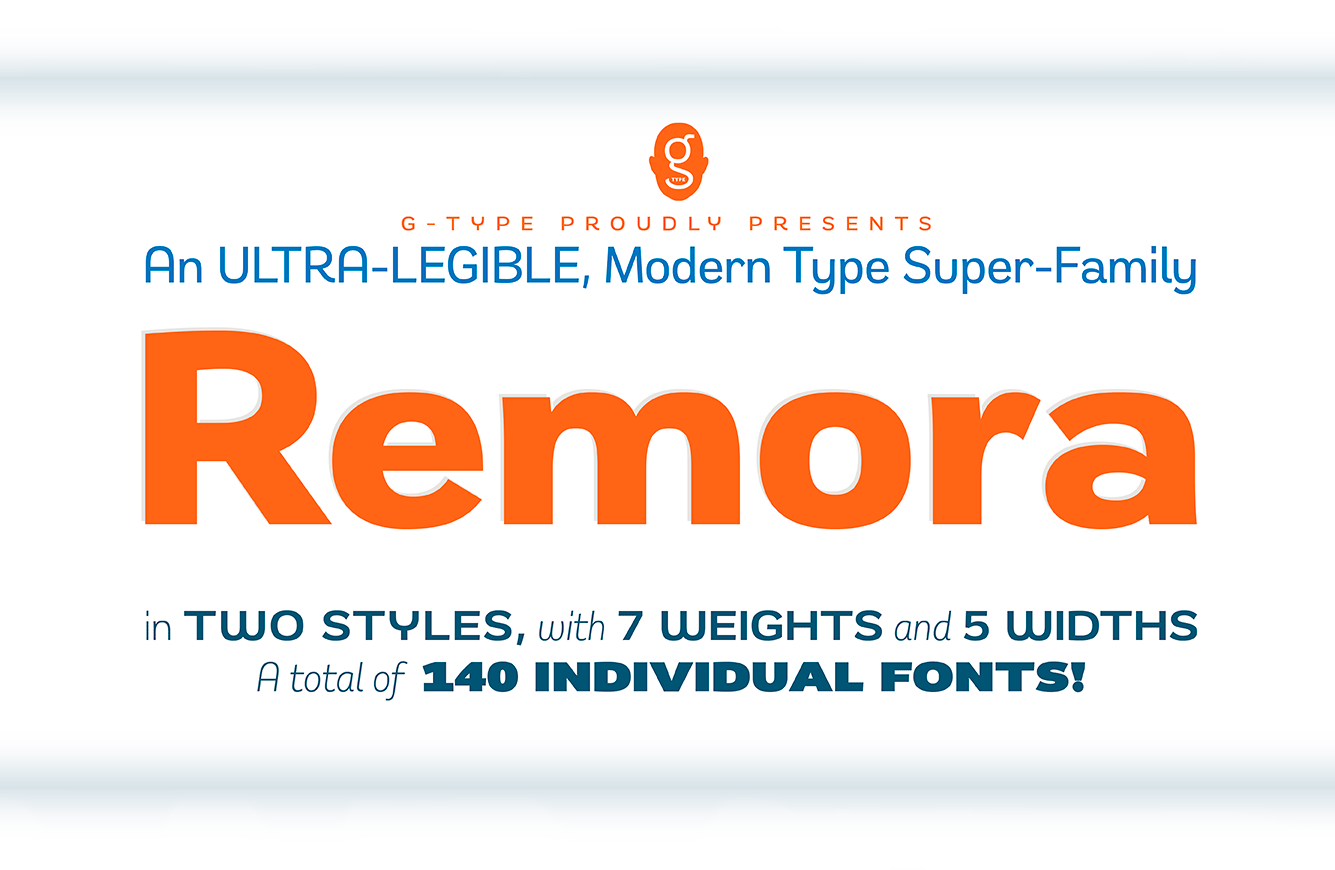
Remora Sans Font Family – Download Grátis
A Remora Sans Font Family é uma oferta gratuita que inclui uma família de 70 fontes perfeitas para suas próximas projemas de design. O designer Hamilton apresenta um tipo humanista sans serif extenso chamado Remora, com duas variações de estilo: Remora Sans e sua versão empresarial, a Remora Corp. Esta famosa familia oferece sete comprimentos individuais (desde Condensada W1 até extra larga W5) para cada uma dessas duas variações. Além disso, Remora possui 7 pesos diferentes – que vão desde Finho até Ultra, e é o tipo mais versátil de super família do mercado, com um total de 140 fonts únicas. A Remora Sans é exuberante e carrega a personalidade, enquanto a Remora Corp é adequada para o design empresarial, fornecendo uma solução perfeita para qualquer necessidade typográfica ou brief de projeto.